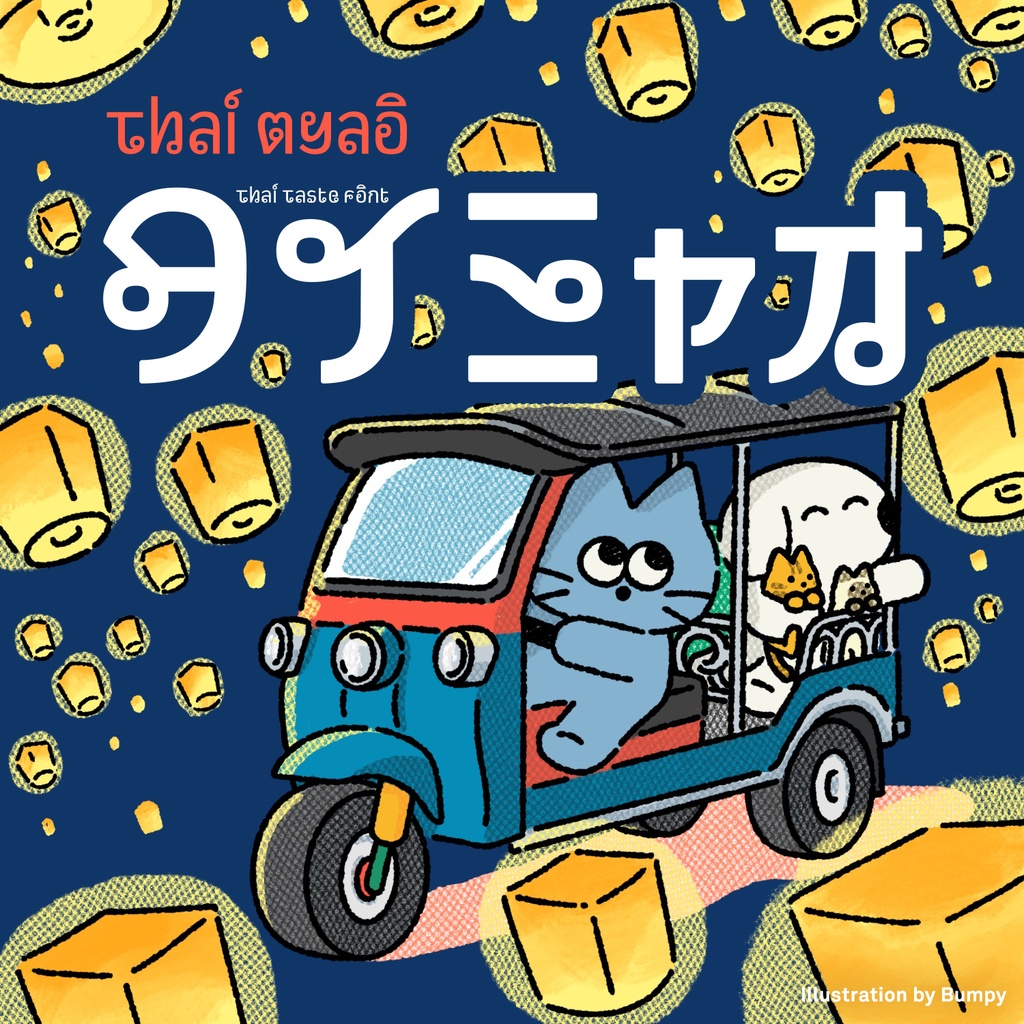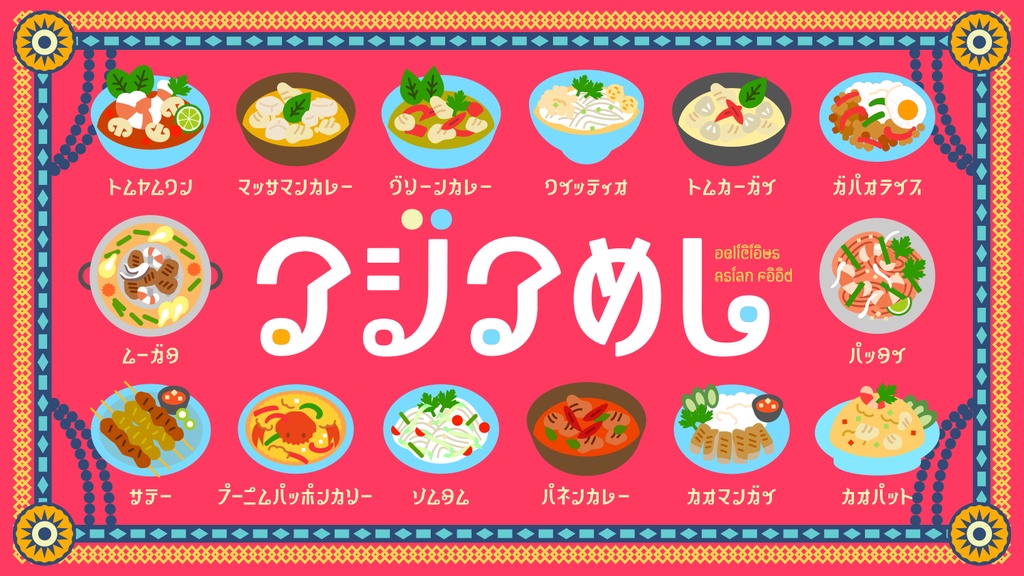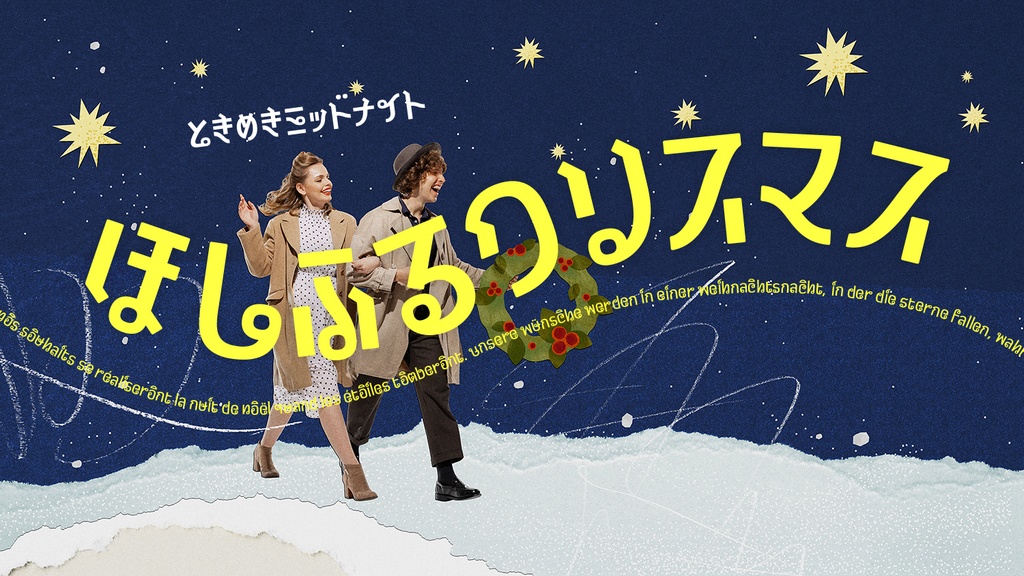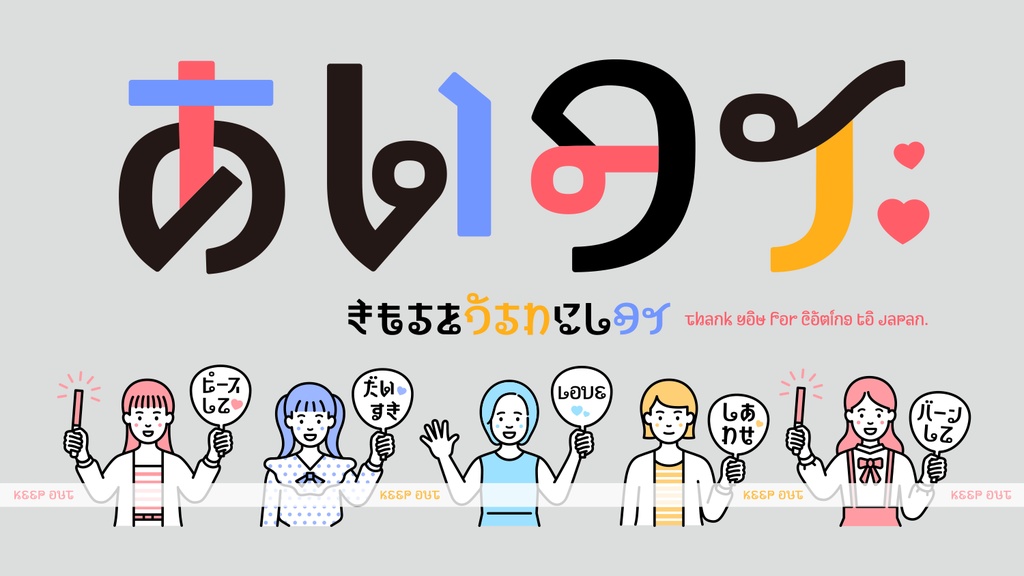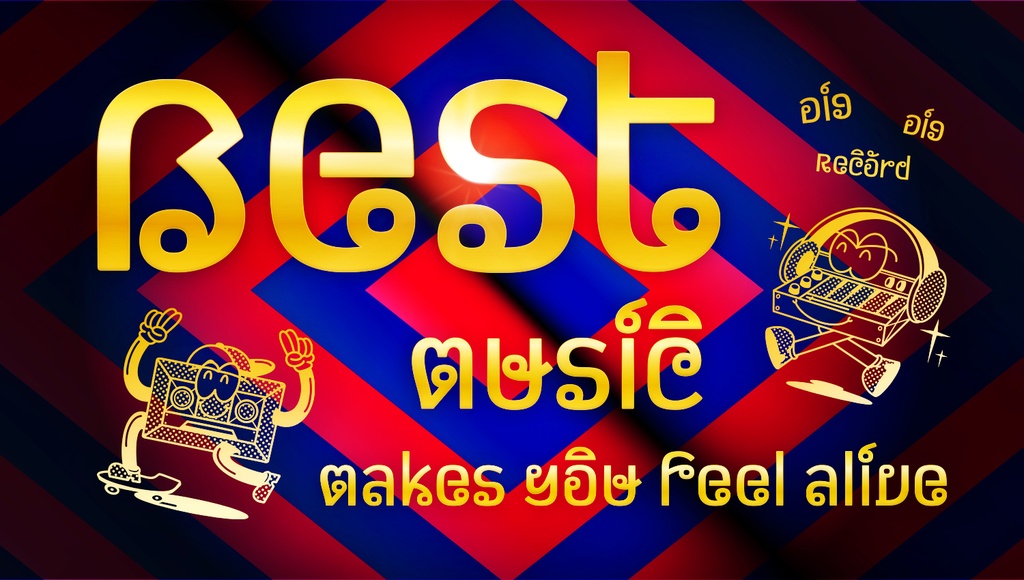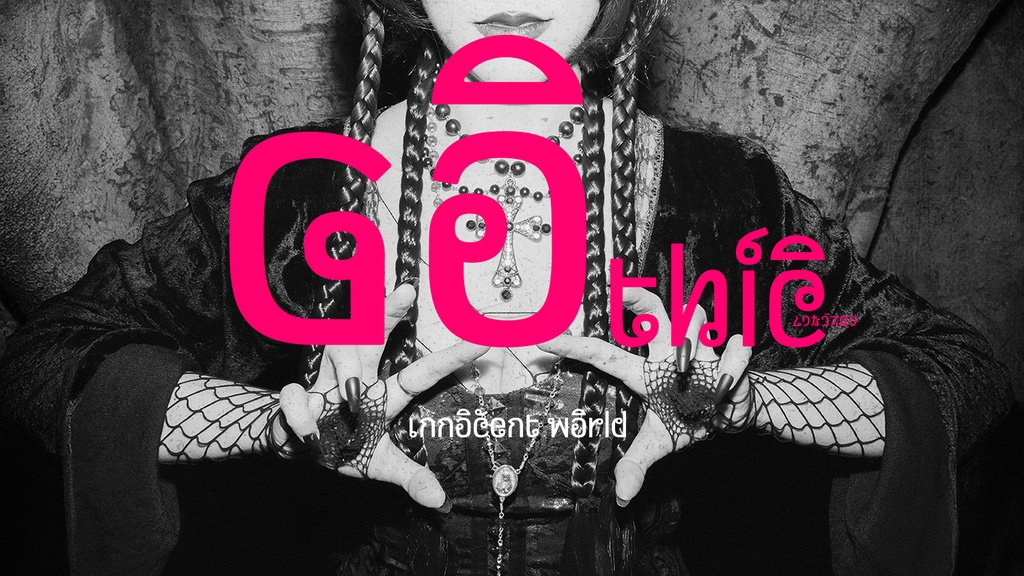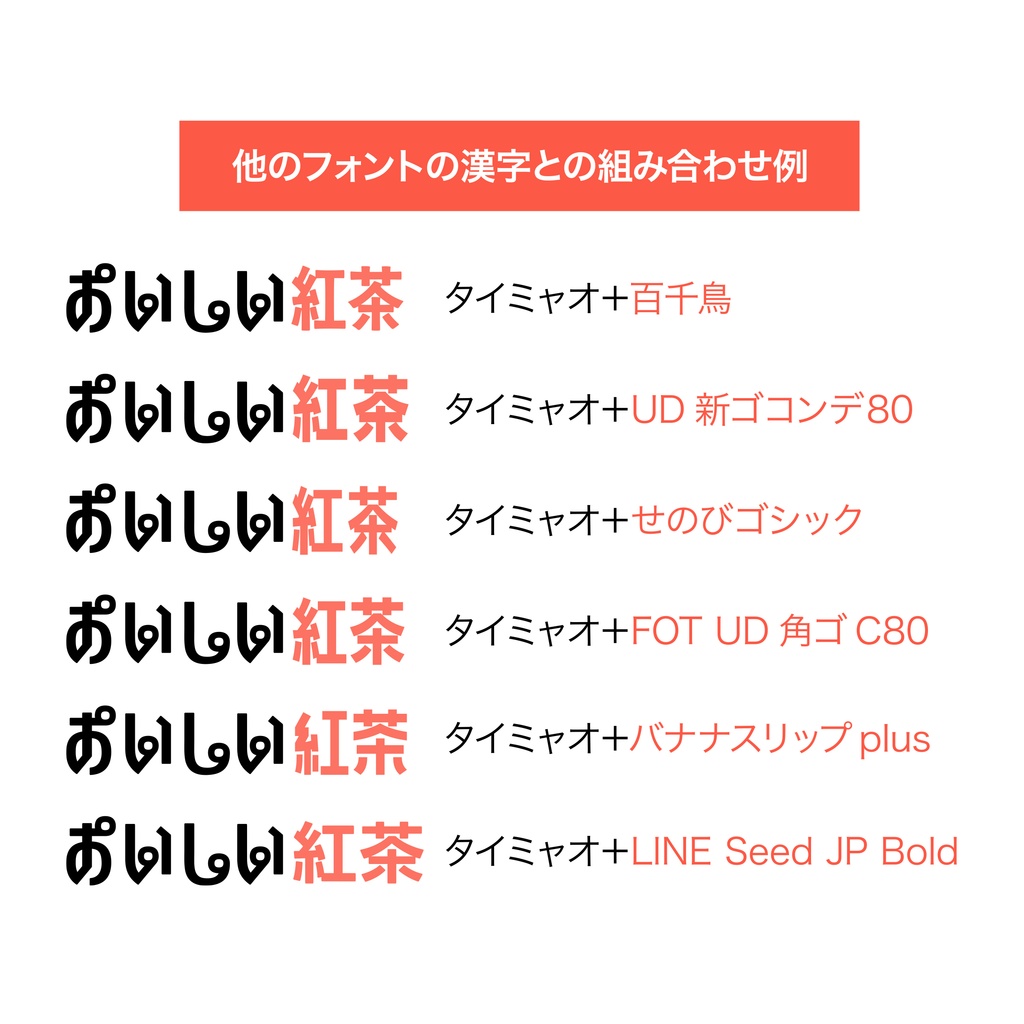
タイミャオ フォント
クルンとした曲線と円形がかわいいタイ風のフォントです。エスニックなデザインや可愛い雰囲気を活かして目を引く楽しいデザインに。英語だけで無くフランス語やドイツ語などヨーロッパの幅広い言語に対応しています。タイ沼推し活にもお使いください。 ■動作環境 Mac:システム/OS X対応(10.x)〜最新のOS X Windows:OS/Windows7〜11以降 フォント形式:OpenTypeフォント 1商品(1ライセンス)につき1ユーザー1PCのみがご利用いただけます。人数分をご購入ください。 ■収録文字について タイミャオ収録文字数688字。※収録文字はアルファベット、ひらがな、カタカナ、約物の一部、西欧諸語、中欧諸語、東南欧諸語、南米諸語。漢字は収録されていないのでAdobe Illustrator、Adobe InDesignなどで任意の漢字のあるフォントを組み合わせてご利用ください。 【収録グリフ】AÁĂÂÄÀĀĄÅÃÆǢBCĆČÇĈĊDĎĐḌÐEÉĚÊËĖÈĒĘẼƏFGĞĜĢĠHĦḪĤḤIIJÍÎÏİÌĪĮĨJĴKĶḴLĹĽĻḶḸḺŁMṀṂNŃŇŅṄṆṈÑOÓÔÖÒŐŌØÕŒPÞQRŔŘŖṜṞSŚŠŞŜȘṢẞTŤŢȚṬṮUÚŬÛÜÙŰŪŲŮŨVWẂŴẄẀXYÝŶŸẎỲỸZŹŽŻẒẔꞋaáăâäàāąåãæǣbcćčçĉċdďđḍðeéěêëėèēęẽəfgğĝģġhħḫĥḥẖiıíîïìīįĩijjȷĵkķḵlĺľļḷḹḻłmṁṃnńňņṅṇṉñoóôöòőōøõœpþqrŕřŗṝṟsśšşŝșṣßtťţțṭṯuúŭûüùűūųůũvwẃŵẅẁxyýŷÿẏỳỹzźžżẓẕꞌあぁいぃうぅえぇおぉかゕがきぎくぐけげゖこごさざしじすずせぜそぞただちぢつっづてでとどなにぬねのはばぱひびぴふぶぷへべぺほぼぽまみむめもやゃゆゅよょらりるれろわゎゐゑをんゔアァイィウゥエェオォカヵガキギクグケヶゲコゴサザシジスズセゼソゾタダチヂツッヅテデトドナニヌネノハバパヒビピフブプヘベペホボポマミムメモヤャユュヨョラリルレロワヮヷヰヸヱヹヲヺンヴ0123456789、︑。︒・.,:;…!?·•*#/\-–—_(){}[]„“”"'@&¶§©®™°|¦†‡゙゚ー ■安心して使えるロイヤリティフリーの書体 商用・デザイン用途(印刷物・ゲーム・アプリ・映像・動画・ロゴ・同人作品)に使用できる、商用申請の必要のないロイヤリティフリーの書体になります。文字の加工・変形も可能です。ご安心ください。 ■OpenType機能 詰め組み機能 ペアカーニング(仮名・プロポーショナル欧文) 別字形(異体字)※異なる字形を用意しています。